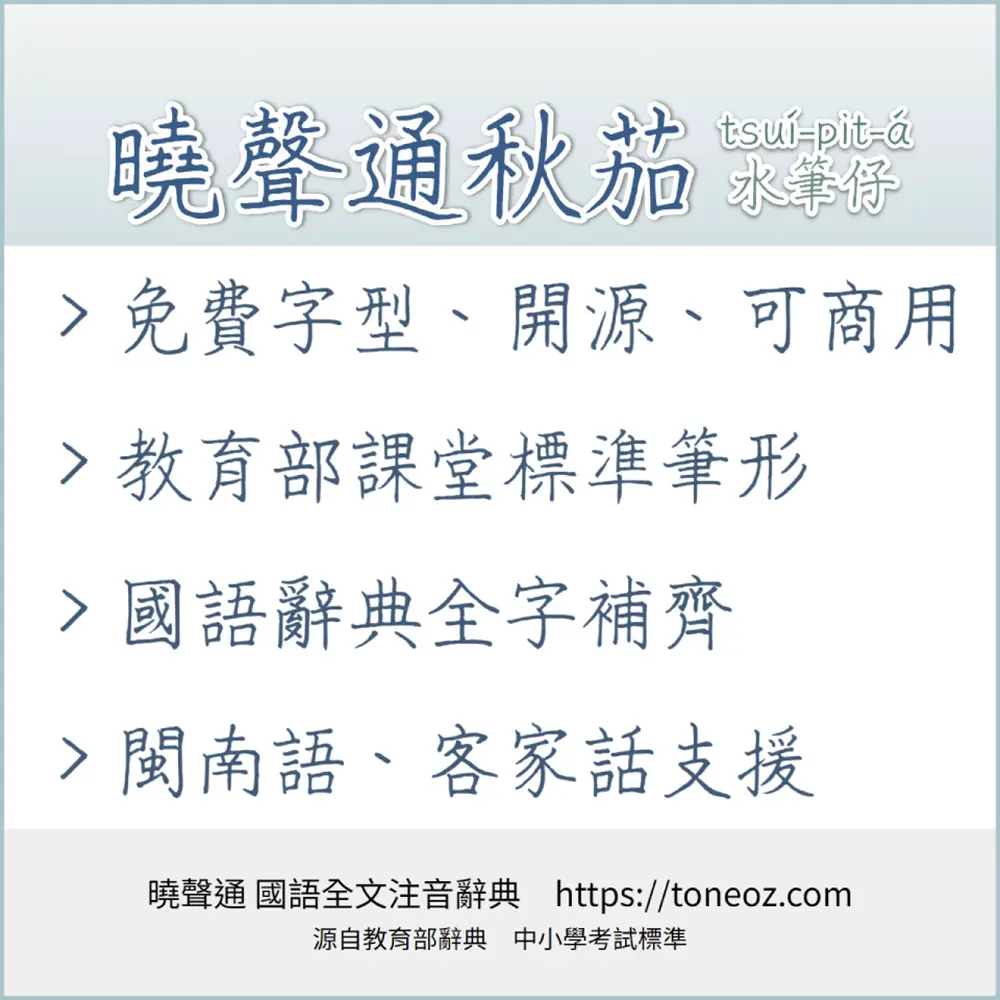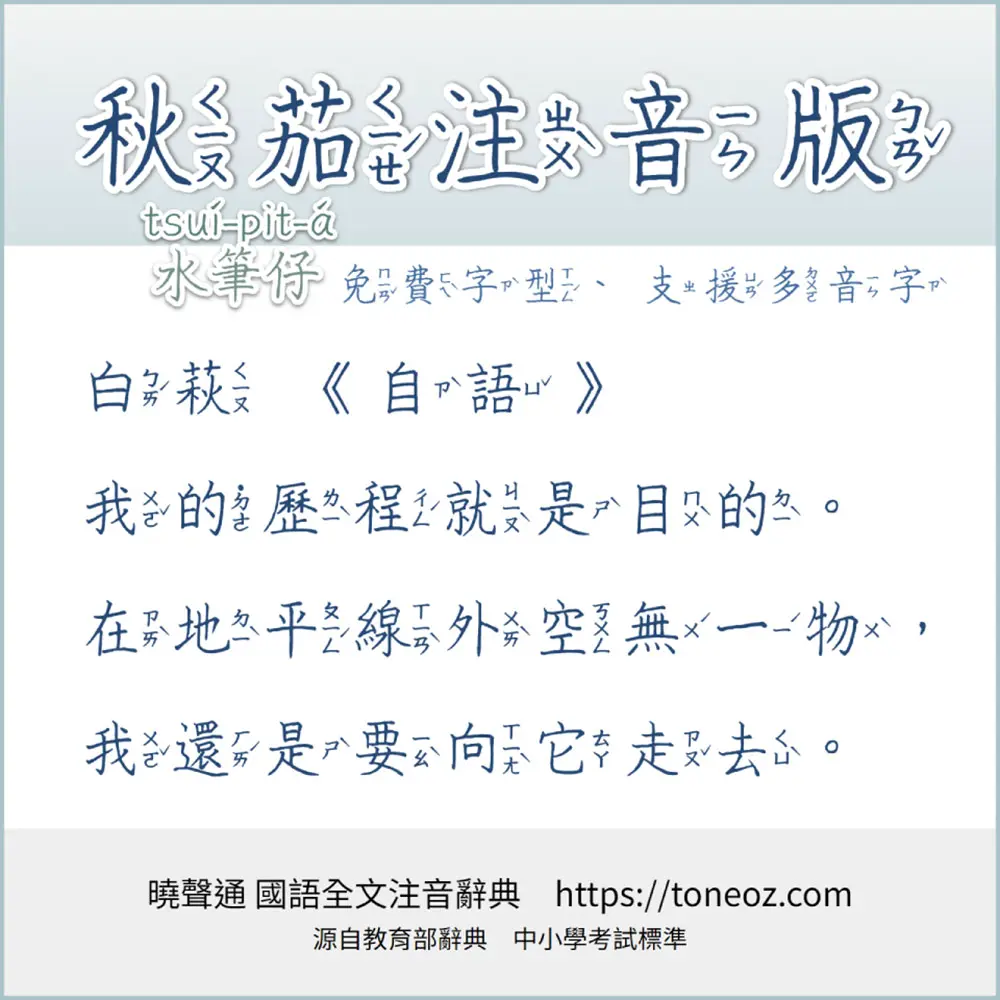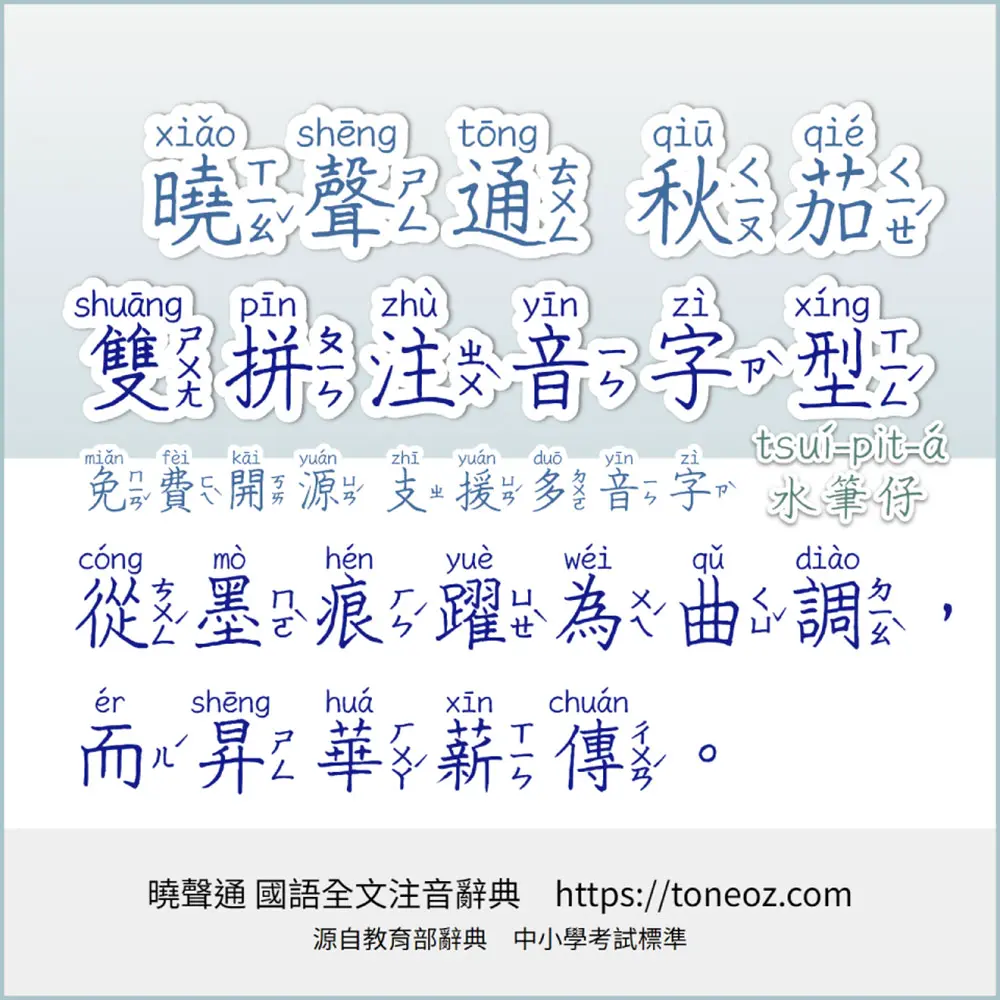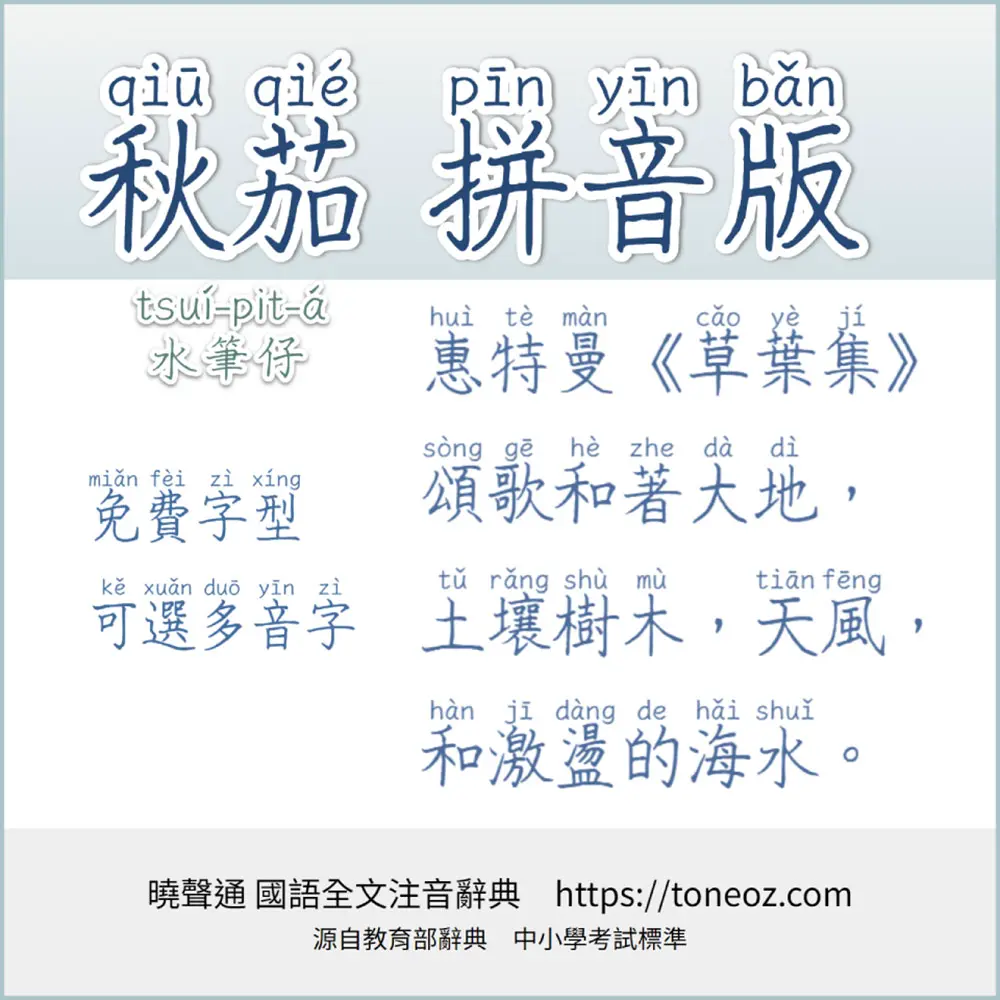
曉聲通「秋茄體」是開源免費的手寫字型,中性簽字筆風格,筆形符合國語教學《教師手冊》,由教育全文注音國語辭典「曉聲通」開發,涵蓋「教育部國語辭典」全條目,中小學考試標準「簡編本」常用字、及「重編本」「成語本」生僻字。以國字標準為前提,支援多元文化教案:閩南語、客家話、日本語、各式拼音、及港澳用字。
「手寫字型」常用於詩詞、歌曲、人物獨白或對話⋯用以提示讀者此段文句建議「以人文角度來思考體會」。
市面上有許多優美的手寫字型:有些草書字型筆跡奔放、有些美術字型筆觸可愛、部分書寫時會參雜不同教育標準或通俗寫法、有些實作四千~九千常用字而有缺字遺憾…以上多少在教學時帶來困擾。
為了輔助教材製作,「曉聲通國語注音字典」開發了「秋茄體(水筆仔)」,來幫助老師們輕鬆創作教案。
曉聲通秋茄體除了標準純漢字版本,另外還有「國語注音」「漢語拼音」及「雙拼注音拼音」多音字型版。
一、曉聲通秋茄體,僅漢字版(ToneOZ-Tsuipita-TC)
二、曉聲通秋茄體,注音版(ToneOZ-Zhuyin-Tsuipita-TC)
三、曉聲通秋茄體,拼音版(ToneOZ-Pinyin-Tsuipita-TC)
四、曉聲通秋茄體,雙拼注音拼音版(ToneOZ-YinPZ-Tsuipita-TC)